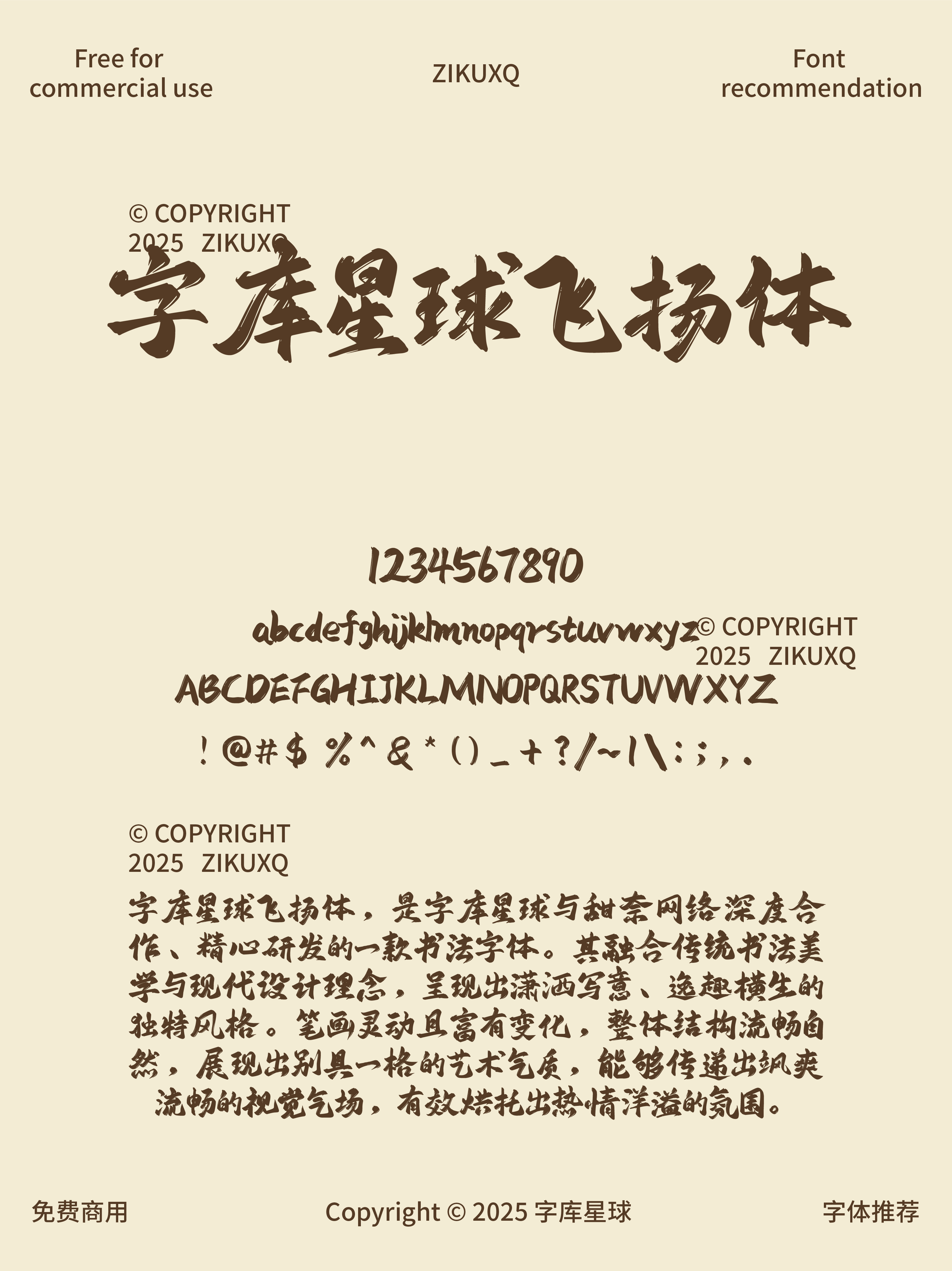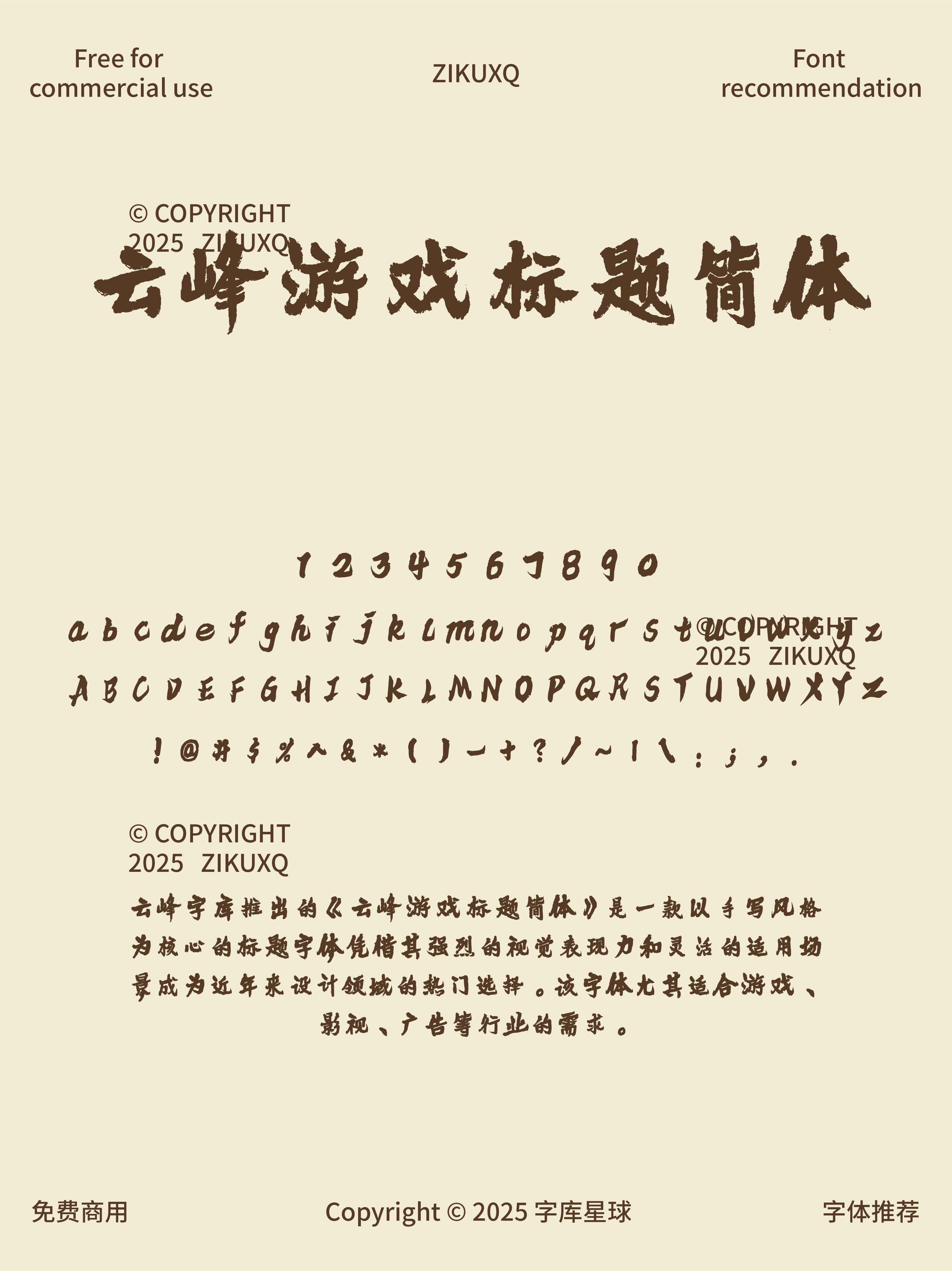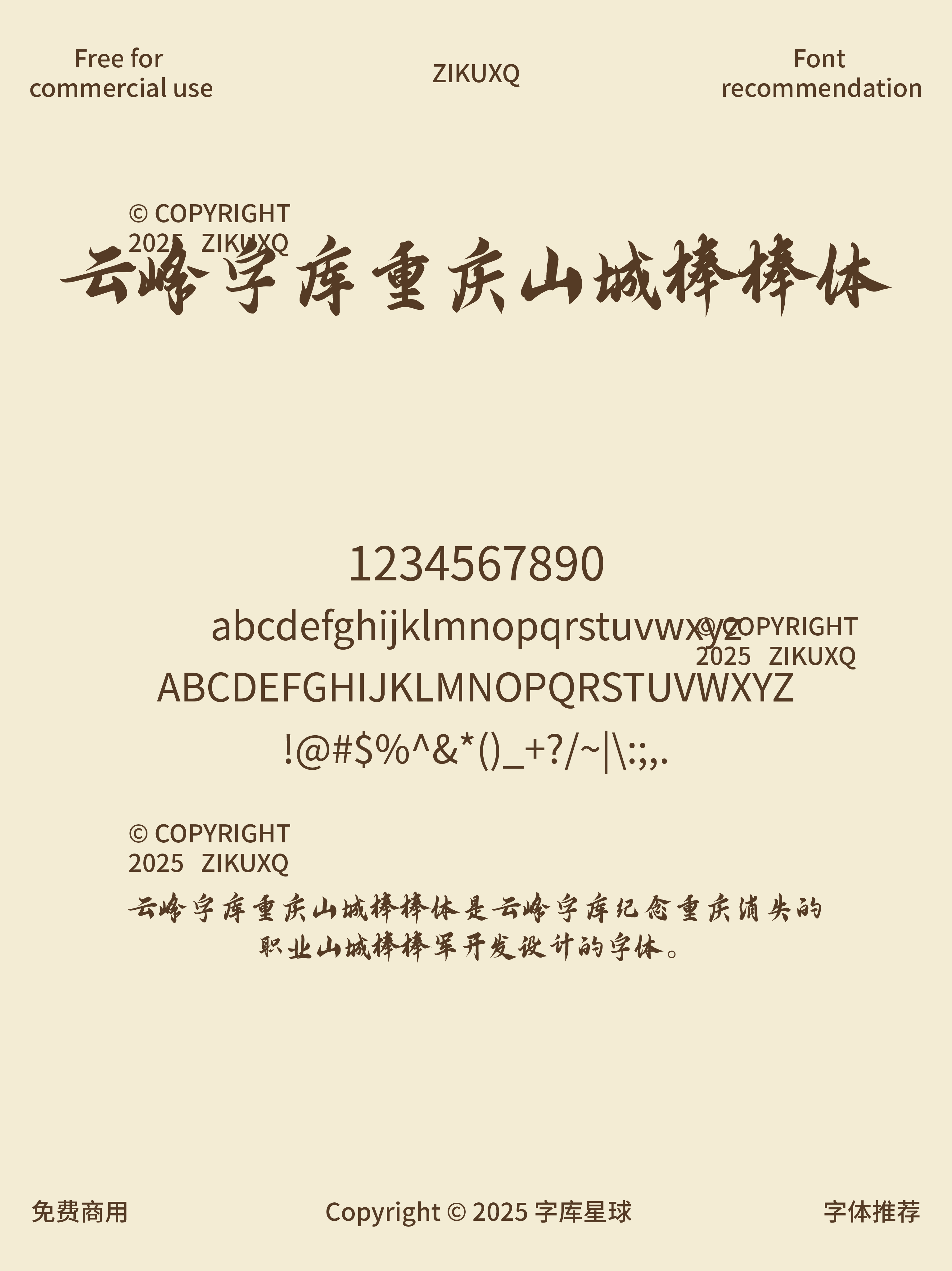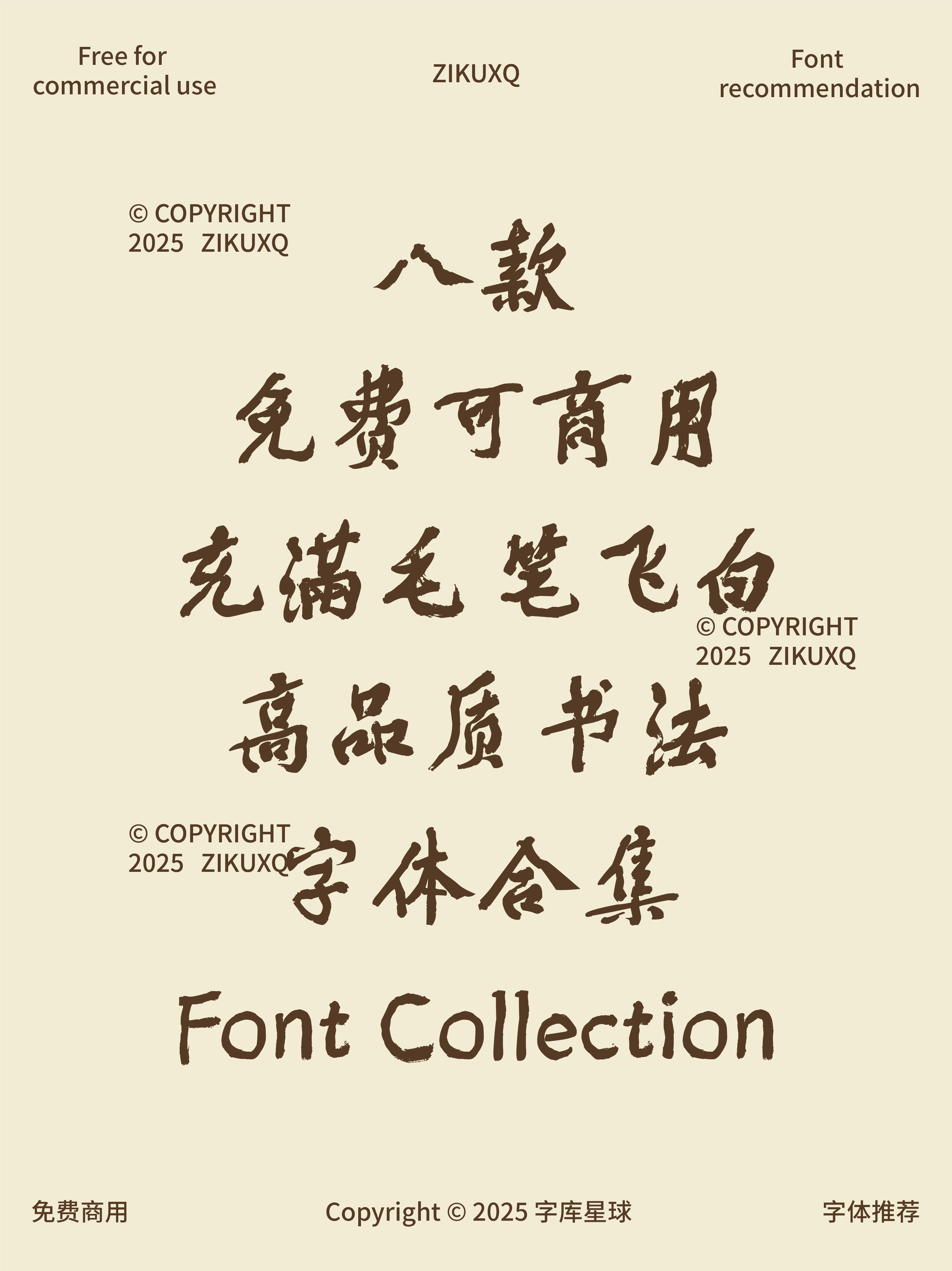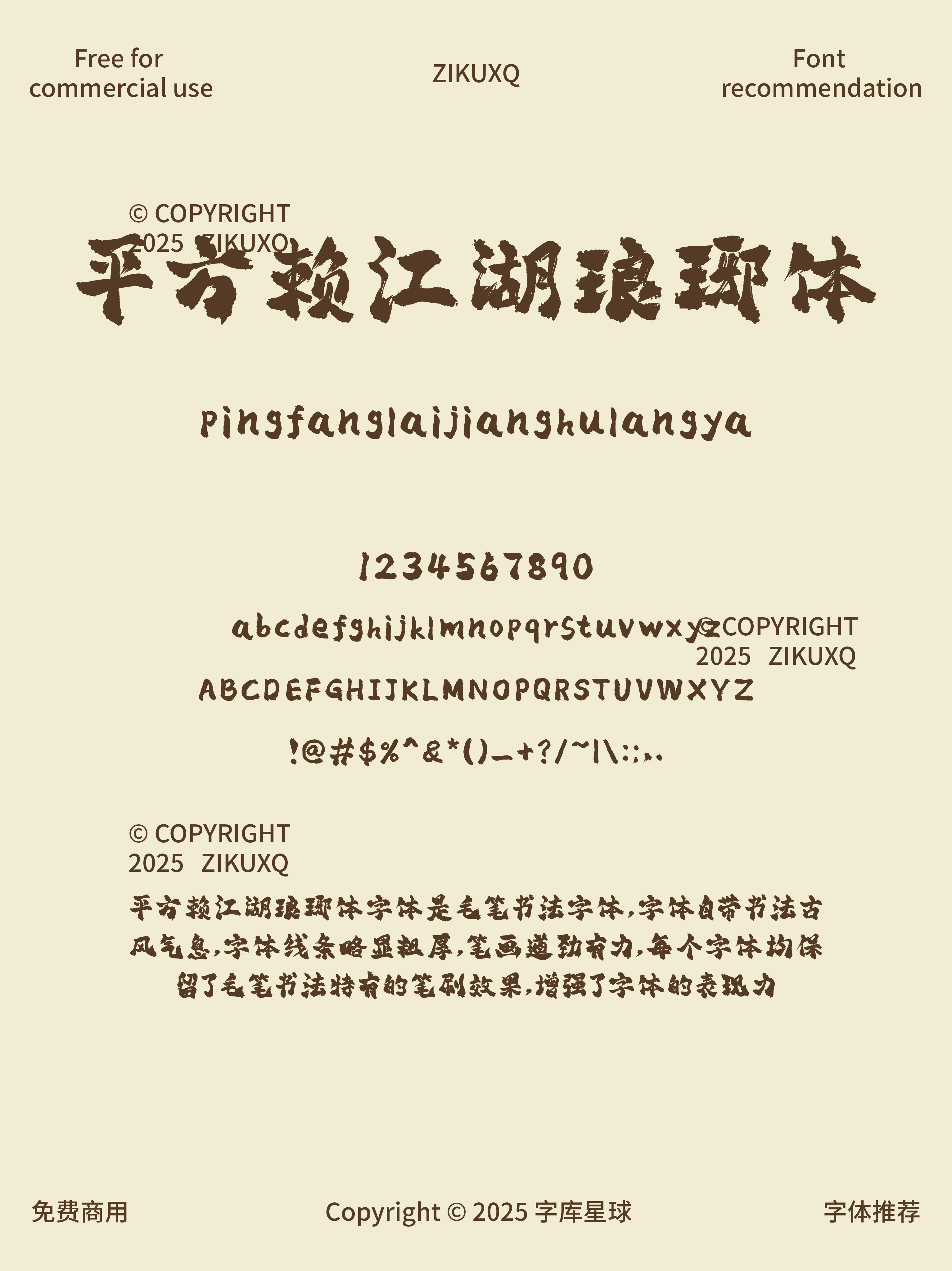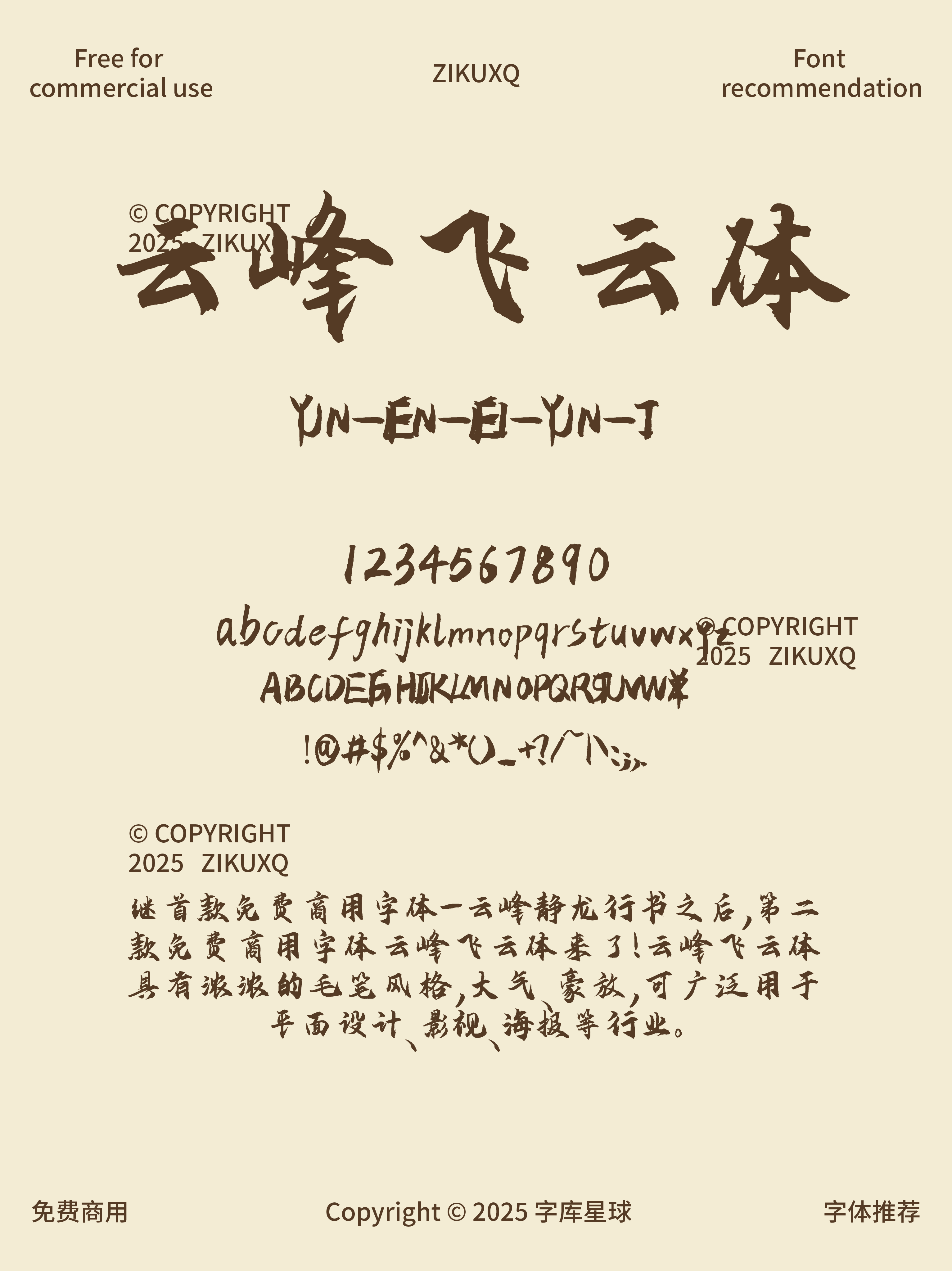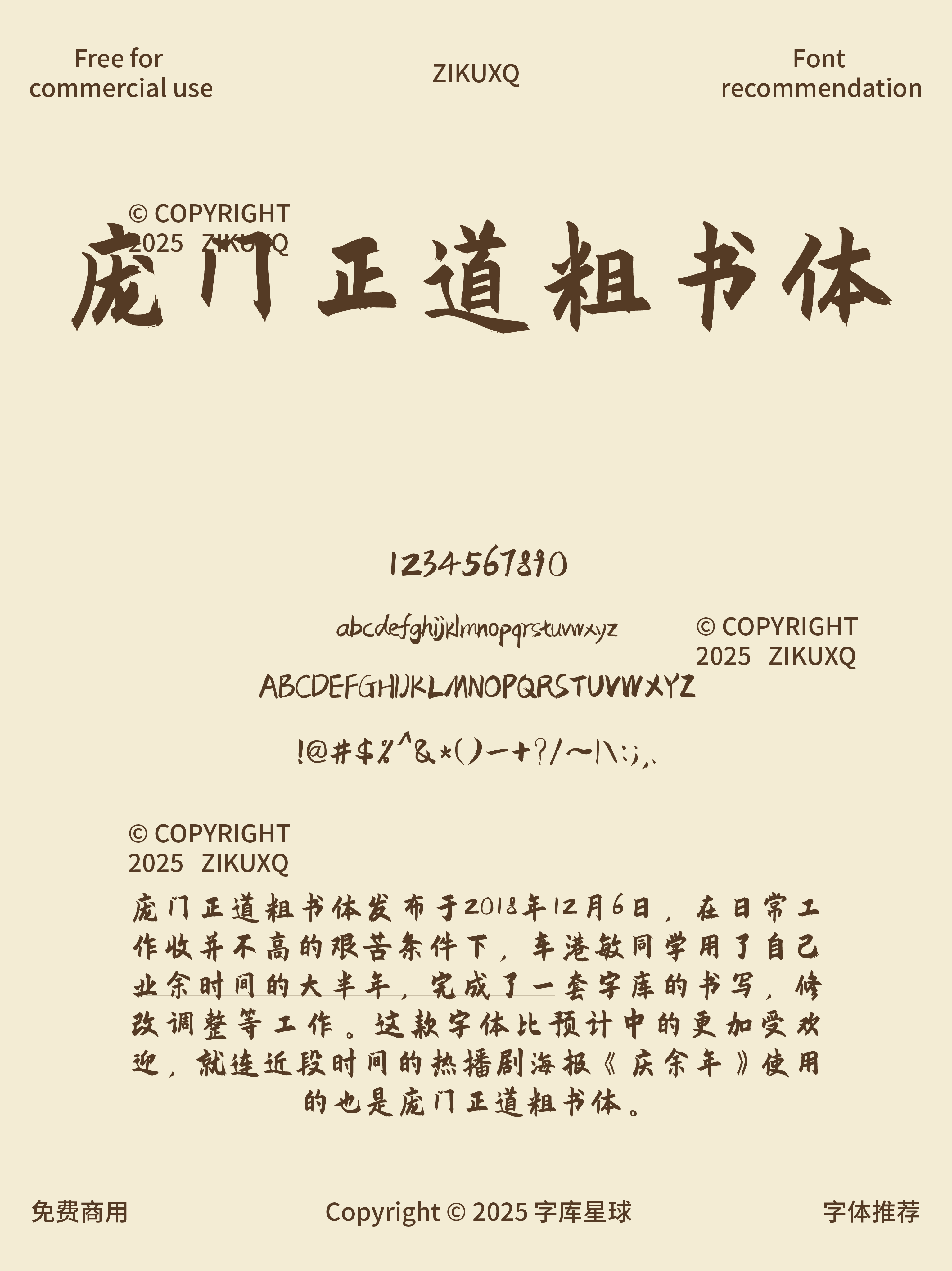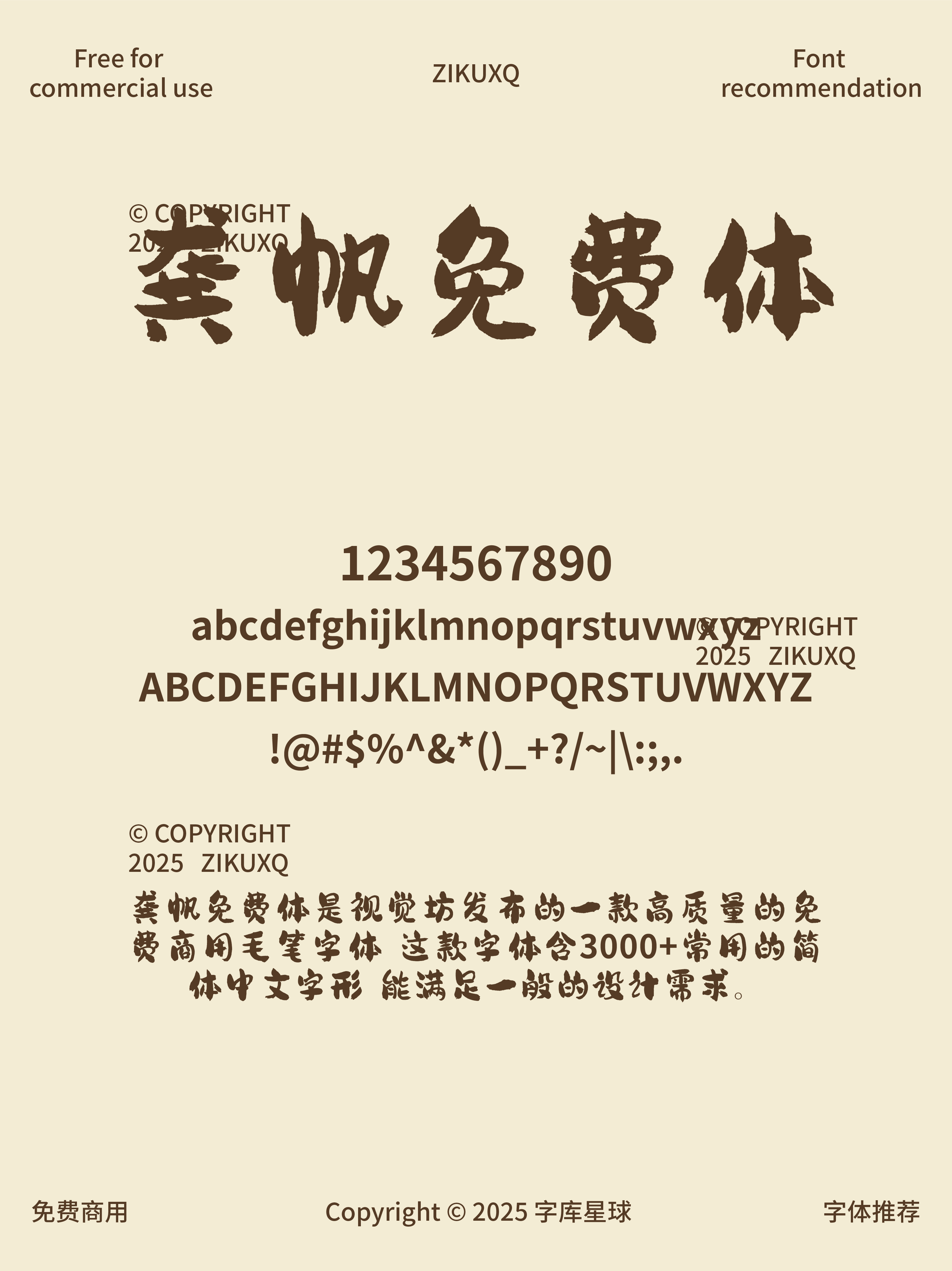
八款免费可商用充滿毛笔飞白高品质书法字体
今天必须给大家分享八款免费可商用且充满毛笔飞白效果的高品质书法字体,让你的设计瞬间格调拉满!
毛笔风格浓郁,字体大气豪放。飞白效果增添了它的潇洒之感,笔画有着明显的毛笔飞白效果,书写风格洒脱自由,笔画粗细对比强烈,视觉冲击力超强。用在艺术设计、平面宣传设计、网页设计上,古典与现代结合的美感立马就有了,像书籍封面、海报设计,选它准没错。
飞白效果在其中起到了画龙点睛的作用,让字体整体更饱满、圆融、浑厚,适用于各类需要体现传统底蕴的商业设计。